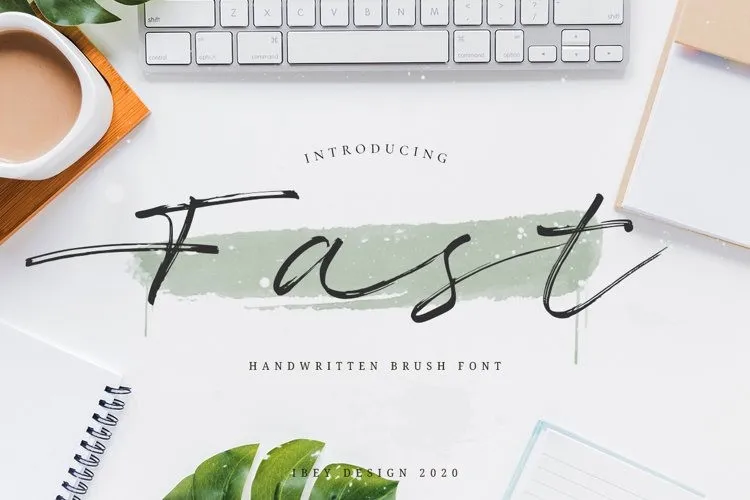
A Fast Font é uma fonte script com estilo contemporâneo que traz a textura de uma ferramenta de pintura para criar design moderno e chamativo. Com sua aparência encantadora, autêntica e descontraída, esta fonte é perfeita para adicionar um toque natural aos seus projetos gráficos. Seja você criando rótulos ou logos para uma empresa de marca, produzindo materiais promocionais ou desenvolvendo designs pessoais, a Fast Font traz um toque autêntico e elegante que se adapta perfeitamente às suas necessidades. Perfeita tanto para design editorial como para publicidade, esta fonte irá adicionar uma personalidade única ao seu trabalho. Seja você criando cartões de visita ou produtos com rótulos, empostos ou até mesmo anúncios em redes sociais, o resultado será um design que se destaca e captura a atenção do público. Com sua textura única e estilo versátil, a Fast Font é uma ótima opção para qualquer projeto que busque adicionar um toque de autenticidade à sua arte digital. Sua facilidade de uso e variedade variada a tornam uma escolha popular entre designers gráficos buscando expressar seus projetos de maneira única e impecável.